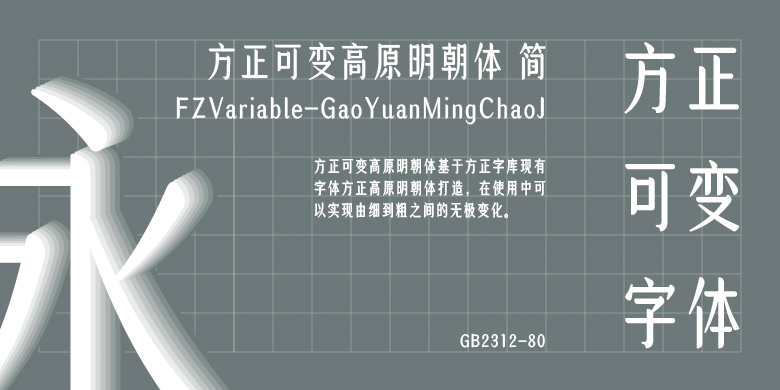
字体名称: 方正可变高原明
方正可变高原明朝体 简
方正可变高原明朝体支持文字粗细无级调节,设计师通过调整字重轴(Weight)的变化,可以实现字形的平滑连续的细微调整,满足不同版式的设计需求。 方正高原明朝体是一款以作者母亲名字命名的字体,字形基于宋体经典且优雅的结构设计而成,减少了宋体具有相对锋芒修饰感的字脚,笔画圆润工整,韵律节奏恰如其分,构建出一款字形修?、匀称、雅韵,极具干练?华之气质美感的家族字体。 此款字体适合时尚、医美、化妆品类行业广告用字及画报杂志标题。